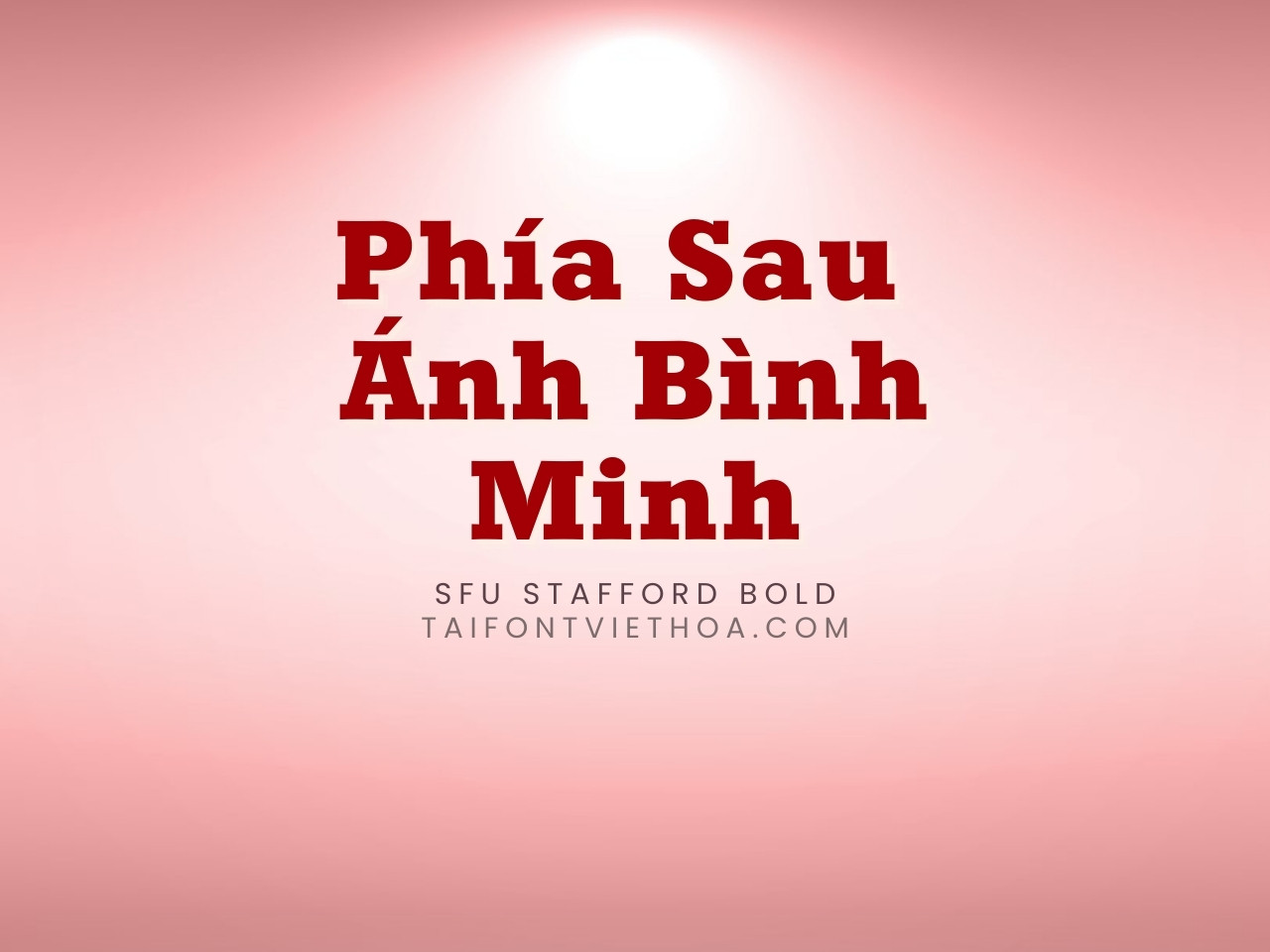
Font việt hóa SFU Stafford
Giới thiệu về font SFU Stafford – Kiểu chữ serif cổ điển thanh lịch và mạnh mẽ
SFU Stafford là phiên bản Việt hóa của một font serif mang phong cách cổ điển với thiết kế thanh lịch, có chân và đường nét rõ ràng. Font lấy cảm hứng từ các kiểu chữ truyền thống của thế kỷ 19, mang đến sự kết hợp hài hòa giữa tính trang trọng và khả năng đọc tốt. Với thiết kế cân đối và các chi tiết tinh tế, SFU Stafford phù hợp cho các dự án cần tạo cảm giác lịch lãm, uy tín và chuyên nghiệp.
Phiên bản Việt hóa do nhóm SFU thực hiện đã bổ sung đầy đủ dấu tiếng Việt, đồng thời giữ nguyên những nét đặc trưng của bản gốc, giúp font hoạt động hiệu quả trong mọi ngữ cảnh thiết kế tiếng Việt. Taifontviethoa.comđã chọn lọc và giới thiệu SFU Stafford như một lựa chọn hoàn hảo cho các nhà thiết kế, đặc biệt trong các lĩnh vực thương hiệu, xuất bản và thiết kế ấn phẩm cao cấp.
Đặc điểm thiết kế cổ điển và ứng dụng đa dạng của font SFU Stafford
SFU Stafford sở hữu các nét chân sắc nét, độ tương phản giữa nét thanh và nét đậm rõ ràng, cùng với cấu trúc chữ cân đối giúp tăng khả năng đọc. Font thích hợp dùng cho tiêu đề, văn bản in ấn, logo thương hiệu hoặc các ấn phẩm đòi hỏi sự trang trọng và chuyên nghiệp.
Ứng dụng lý tưởng: sách, báo, tạp chí, bao bì sản phẩm cao cấp, thương hiệu thời trang, thiết kế nội thất hoặc tài liệu pháp lý. Ngành nghề phù hợp: xuất bản, giáo dục, thời trang, pháp lý, tài chính, nội thất và các thương hiệu theo đuổi hình ảnh uy tín, đẳng cấp và truyền thống.